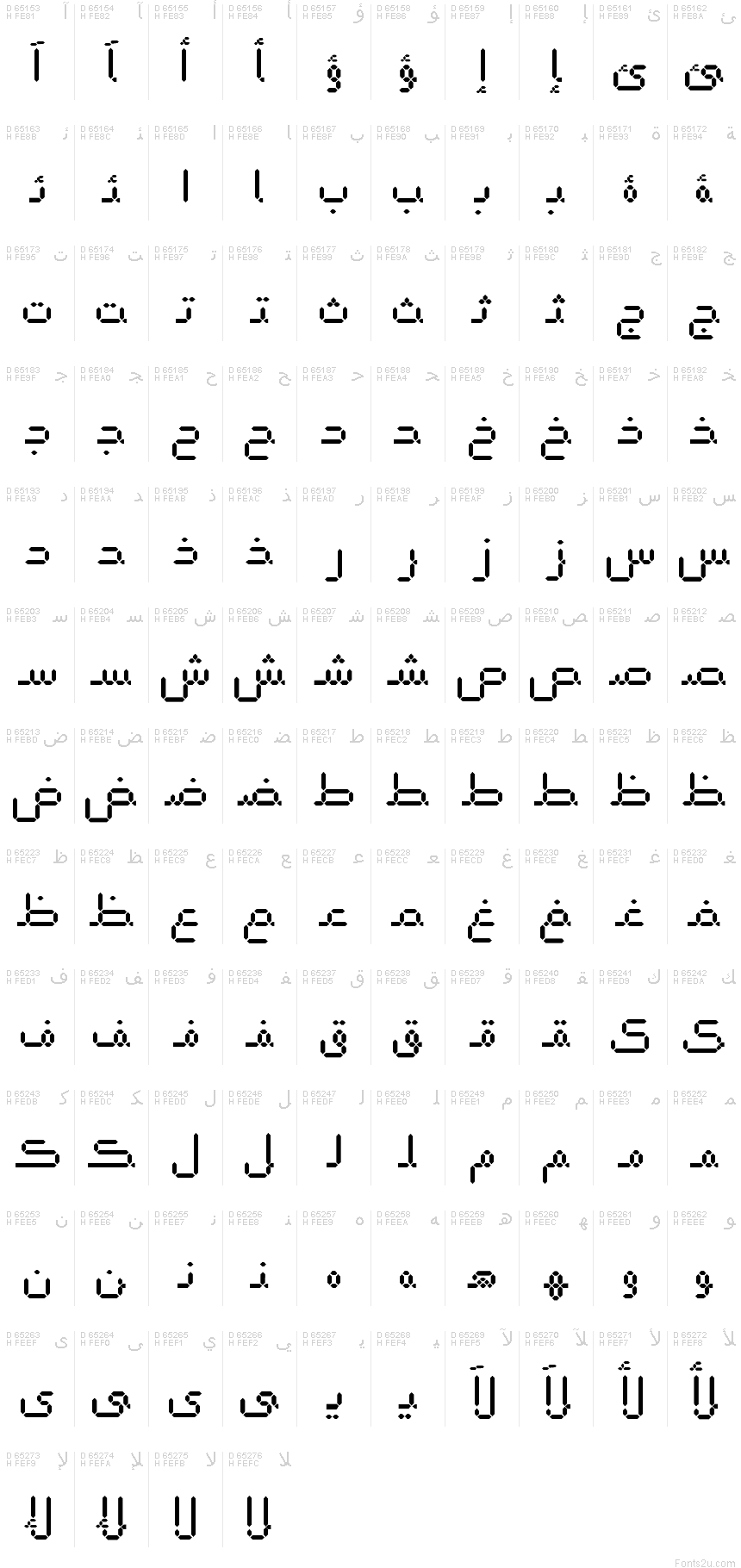
B Elm od Borna Rayaneh je bezplatné digitálne titulkové písmo inšpirované arabským písmom, definované segmentovanými ťahmi, ktoré každé písmeno rozkladajú na ostré, modulárne kúsky. Opakované zárezy a hranaté spoje dodávajú písmenám kódovaný, takmer signálny rytmus, ktorý pôsobí skôr ako špeciálny digitálny displej než ako štandardná typografia.
Táto štruktúrovaná fragmentácia sa hodí pre technologický branding, experimentálne plagáty, grafiku inšpirovanú UI, hudobné vizuály a herné prekryvné prvky (overlays), kde mechanický tón pomáha nastaviť atmosféru. B Elm dokáže podčiarknuť krátke titulky, úvodné kartičky alebo koncepty log, najmä tam, kde bezplatné písmo s výrazne digitálnym nádychom pomáha textu pôsobiť ako skonštruovaný, a nie napísaný.
Mapa znakov písma B Elm
Mapa znakov písma B Elm: Arabské prezentačné formy-B, strana 1
Glyfy písma B Elm — Arabské prezentačné formy-B, strana 1